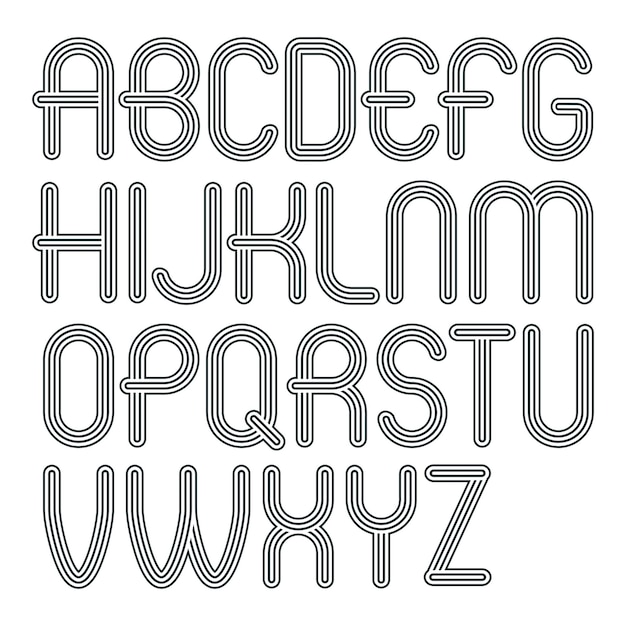
Набор диско-векторных букв английского алфавита в верхнем регистре изолирован. Обалденный округлый шрифт, машинопись для использования в дизайне логотипа. Создан с использованием геометрических тройных полос.Набор диско-векторных букв английского алфавита в верхнем регистре изолирован. Обалденный округлый шрифт, машинопись для использования в дизайне логотипа. Создан с использованием геометрических тройных полос.
Набор диско-векторных букв английского алфавита в верхнем регистре изолирован. Обалденный округлый шрифт, машинопись для использования в дизайне логотипа. Создан с использованием геометрических тройных полос.